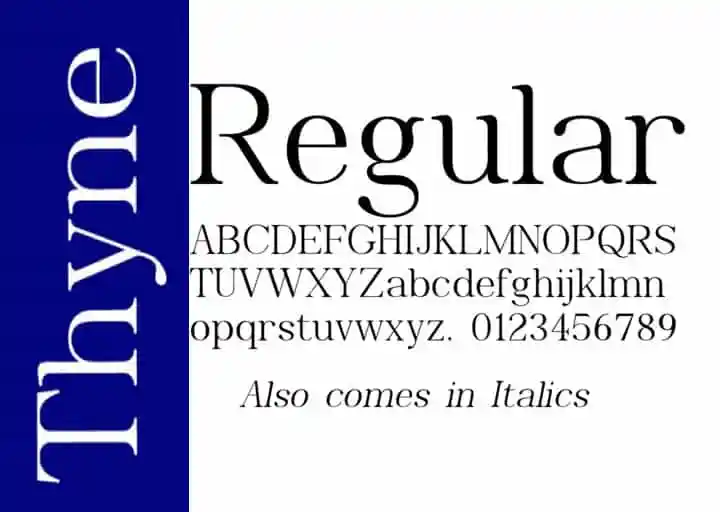
Thyne Serif Font – Fonte Grátis
Thyne Serif Font
A Thyne Serif Font é uma fonte serif que se destaca pela elegância e sofisticação moderna criada por Typotheticals. Esta fonte moderna e sofisticada traz um toque luxuoso a qualquer projeto, seja ele para jornais, mídias sociais, marcações ou logotipos. Suas linhas finas e detalhes cuidadosos dão uma aparência única e elegante que faz dela uma escolha ótima para projetos com um visual de luxo. Com Thyne Serif Font, seus designs se destacam em qualquer plataforma digital ou impressa, garantindo sempre um toque sofisticado e único no seu trabalho.